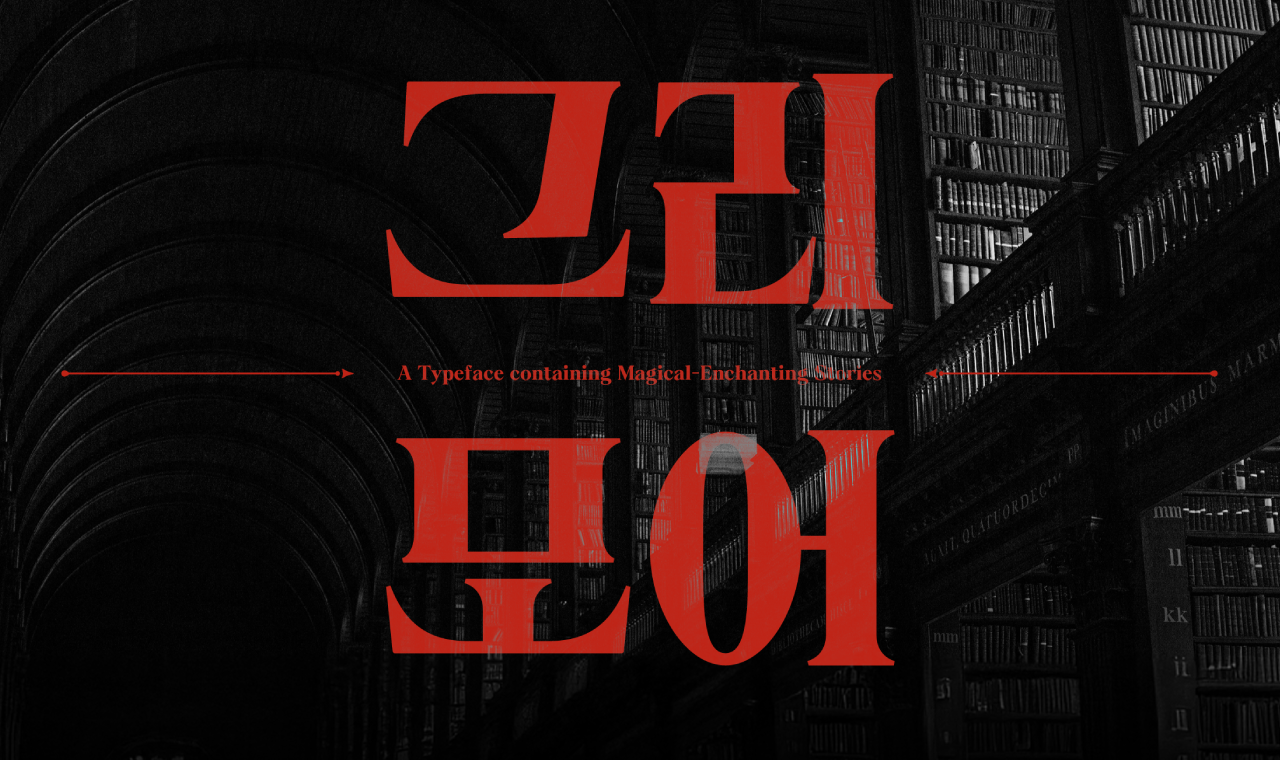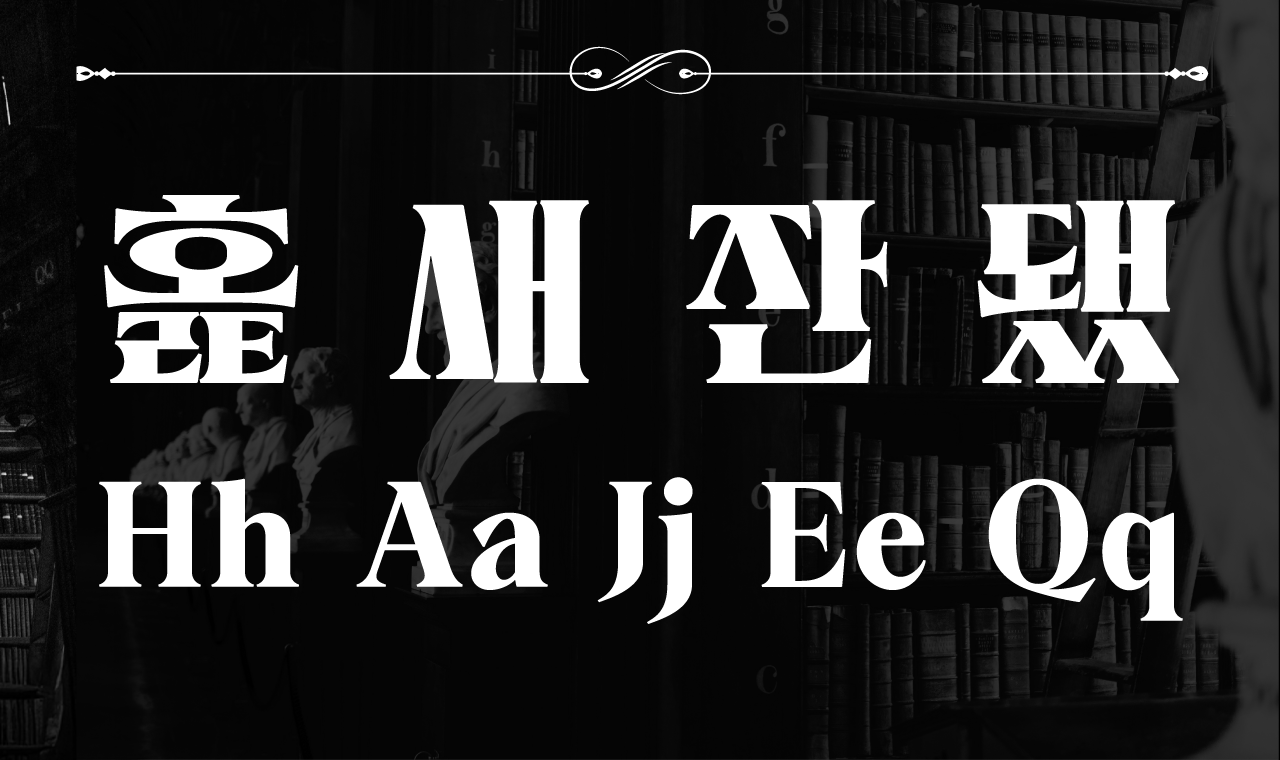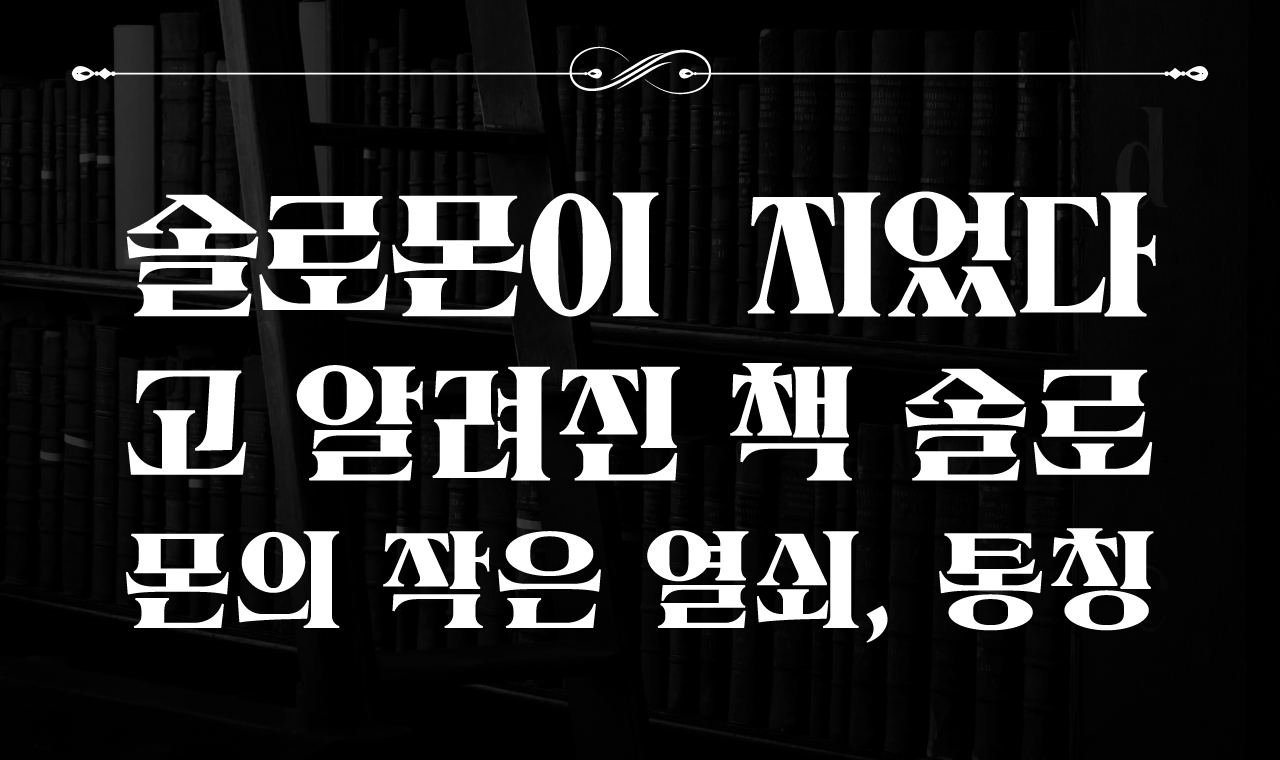
‘그리모어’는 가로, 세로획의 대비가 강하고 날카로운 영문의 세리프를 차용한 점이 특징인 디스플레이 글꼴입니다. 마도서(魔導書)로 번역되는 그리모어는 동화 등에 나오는 긍정적인 의미 속 마법보다는, 마녀, 악마 등과 관련된 흑마법의 뉘앙스를 주로 일컫습니다. 그리모어는 매력적인 악역처럼, 선과 악의 범주가 공존하는 양가적이고 다원화된 창작물 속 특정 캐릭터들의 매력을 돋보이게 하는 데에 탁월합니다.
Yoon 그리모어